楼梯油漆字效果海报如何制作?超级简单的楼梯油漆字效果海报制作方法
时间有限,来看问题吧:
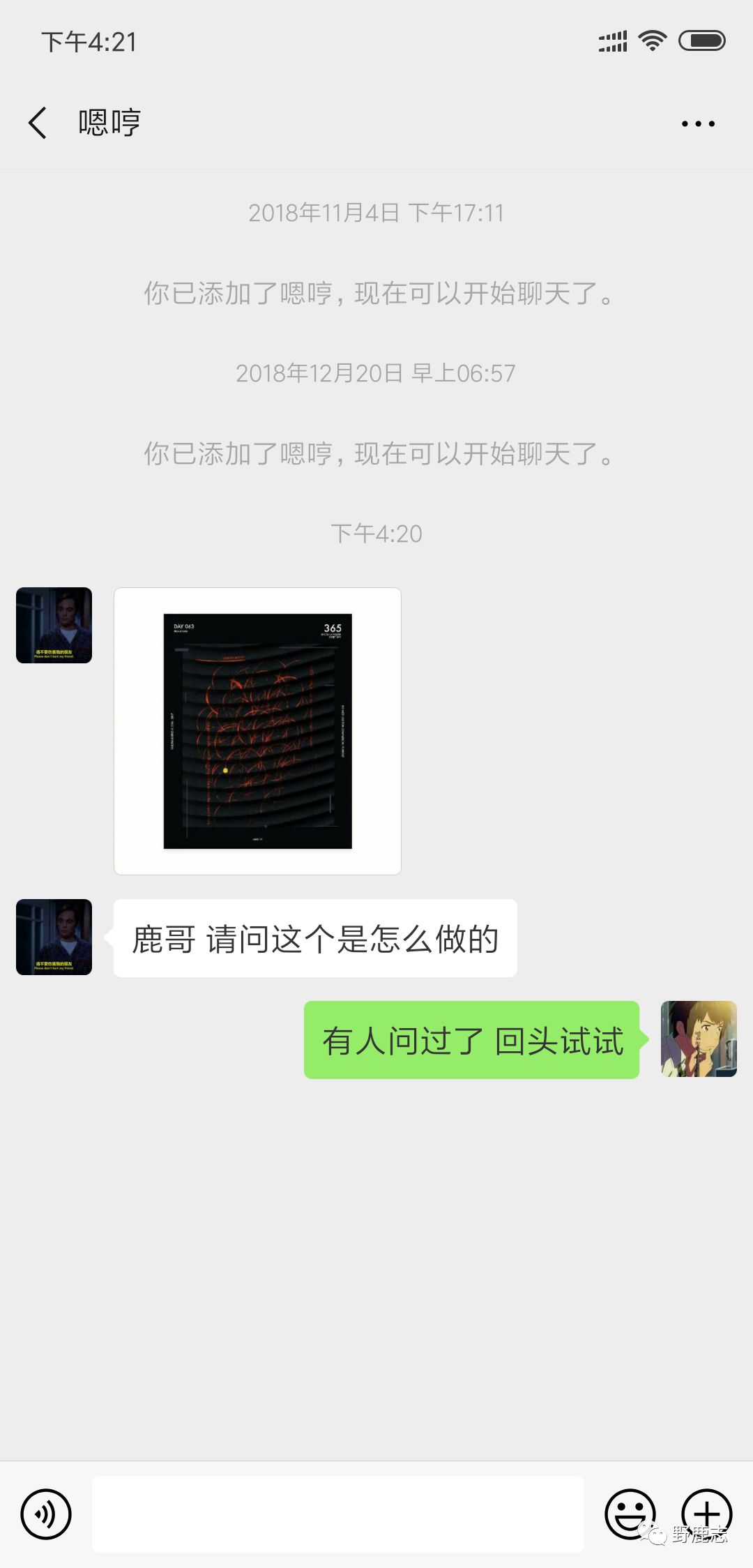
这个好像是国外大神Baugasm的作品吧,他的很多抽象作品其实都没有用到太多复杂的技巧,最重要的是别人的创意牛啊。
这个类似楼梯上油漆字的效果我试了试,其实用平面或者三维软件都能做出来,也是很简单的。
正好又有很久没有写过平面软件的内容了,来吧,今天我们就用Ai和Ps来制作这种楼梯上的油漆字效果海报吧!
首先打开Ai,新建画板,尺寸大家看着办吧:
用椭圆工具画一个圆,描边无填充,颜色随意:
画笔面板打开画笔库,Ai自带了很多很有意思的笔刷的:
找一个你自己觉得合适的笔刷,描边的粗细可以视情况进行调整:
多复制几个圆,尝试着更换不同的笔刷,随意一点就好,弄完大概这样:
至此Ai里就操作完毕啦,接下来就是在Ps里操作了,先制作阶梯吧,当然你如果用C4D制作也可以。
不过我觉得Ps做一个阶梯也不是很复杂,就用Ps搞了,如图所示画一个椭圆:
重复复制多个椭圆出来,这一步不用说吧:
给椭圆添加图层样式,斜面与浮雕,参数的话大家看着效果来吧,多试试就好,这个真没什么好说的:
再添加一个投影吧,同样看着效果来就好:
再把图层样式复制给其他的椭圆,这样阶梯的效果就出来了:
把椭圆图层盖印出来:
相信大家都知道我后面要怎么做啦,对的,要用一下置换。
先把盖印图层转为智能对象,然后高斯模糊几个像素吧:
另存为置换psd文件:
把Ai里做好的图案直接拖进来:
先给个纯色填充图层,作为该图层的剪切蒙版吧,这样方便观察:
执行置换吧,参数看着办就好:
再调出图层样式,看着效果把下一层的黑色往右移动一丢丢:
新建空白图层,填充黑色,转为智能对象添加杂色,这一步不用说吧:
将杂色图层混合模式改为滤色,降低不透明度,这样就有颗粒感了:
最后码字排版导样机,老三样看看效果吧:
大概有点那个意思吧,很简单吧,今天无论是内容或者技巧很简单的,适合新手练习,大家一定要动手起来哦。